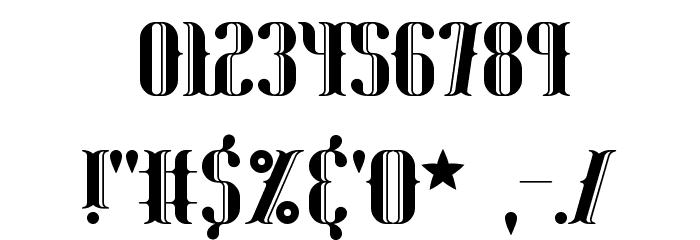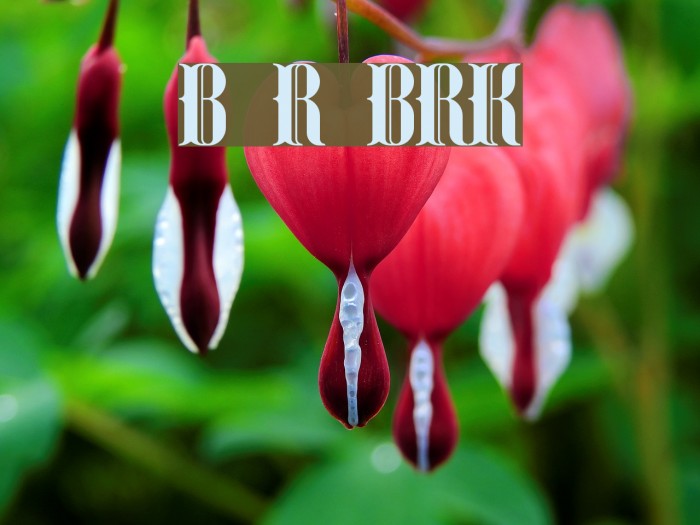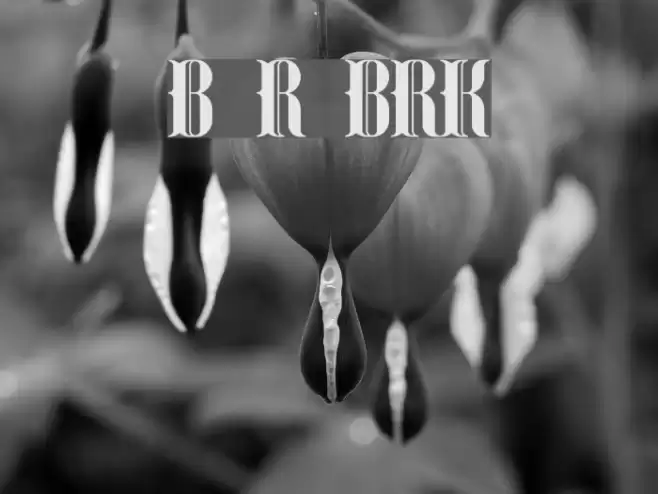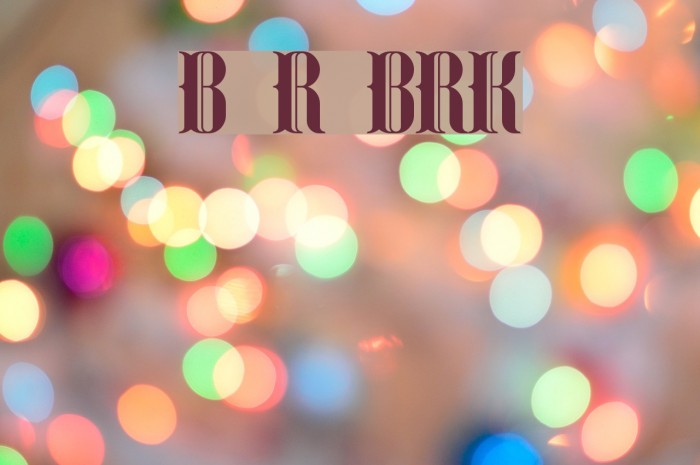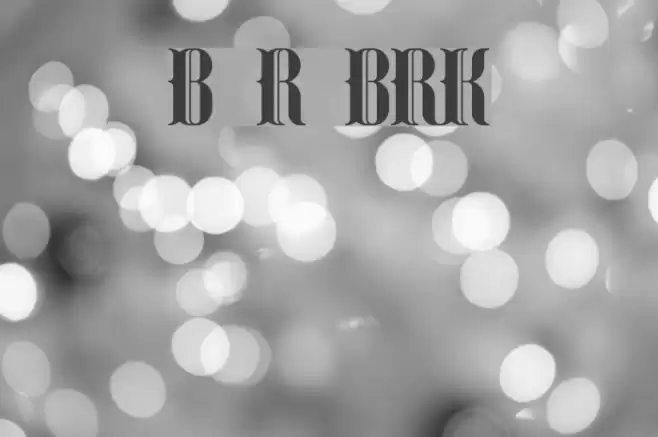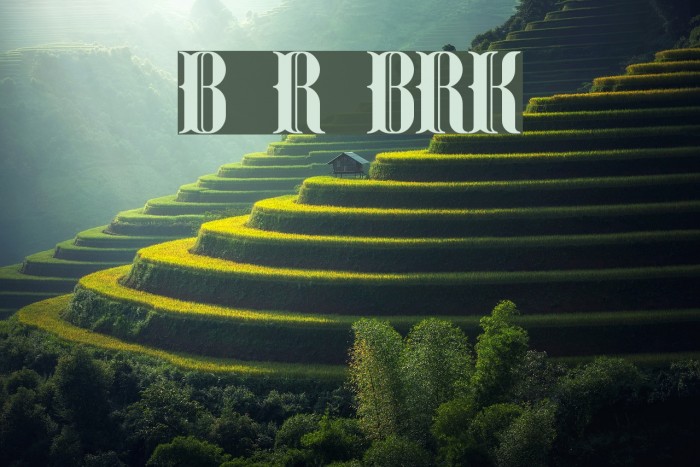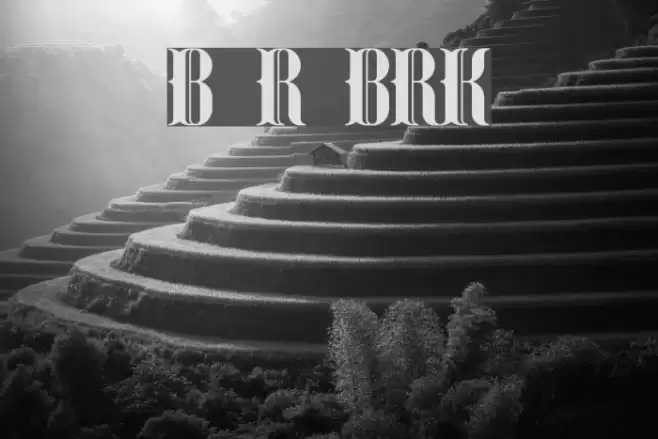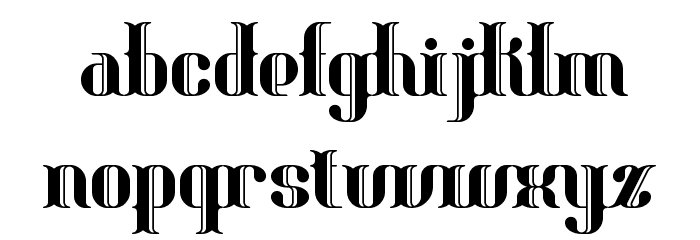
Blackoninaut Redux BRK Font
| Caz de utilizare | Logos, Headlines, Decorative text |
| Proiecte propuse | Ideal for vintage-themed designs, gothic posters, book covers, and branding that requires a historical or dramatic touch. |